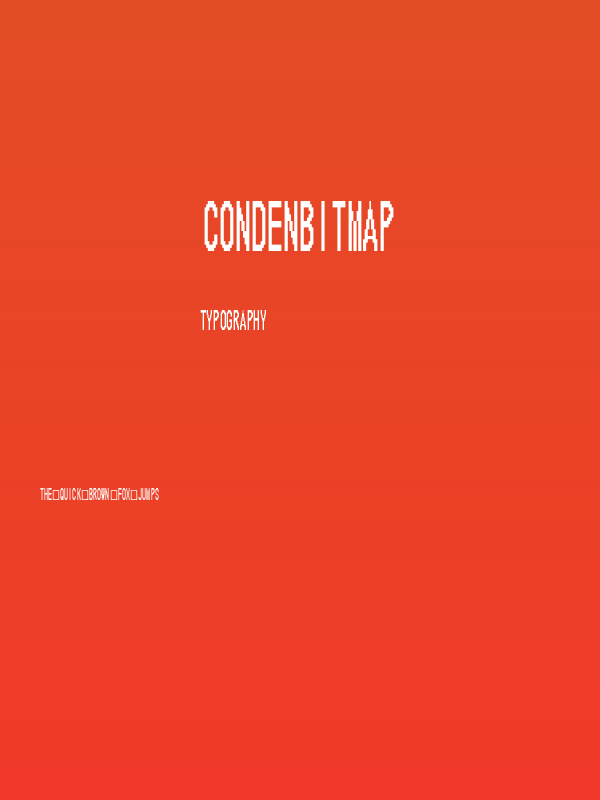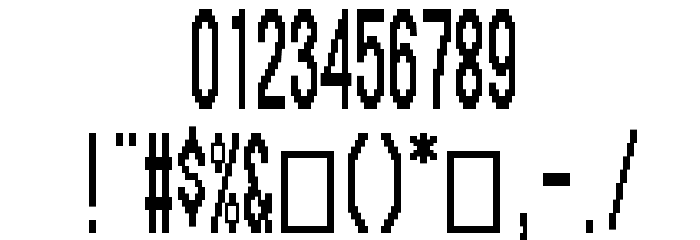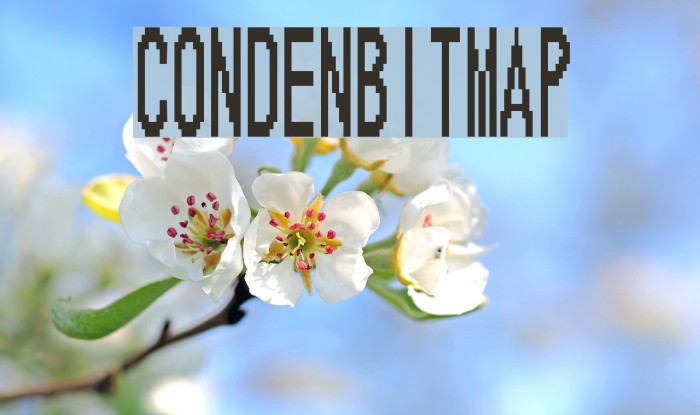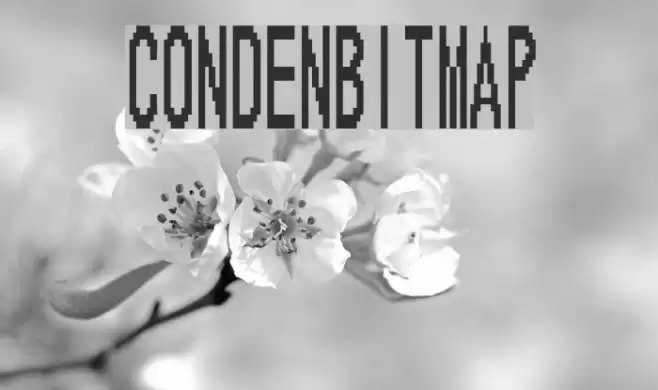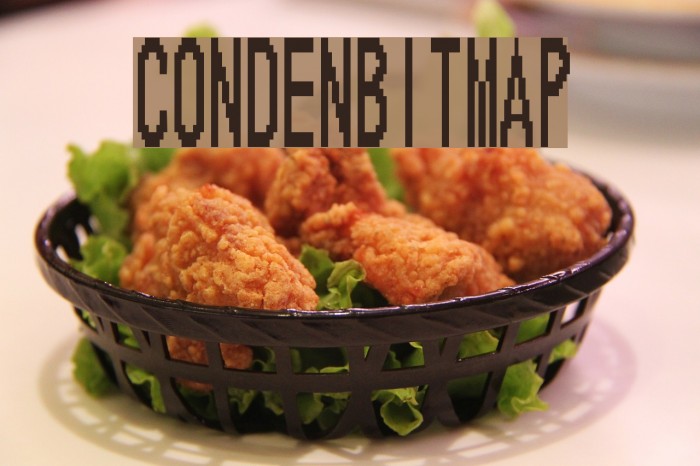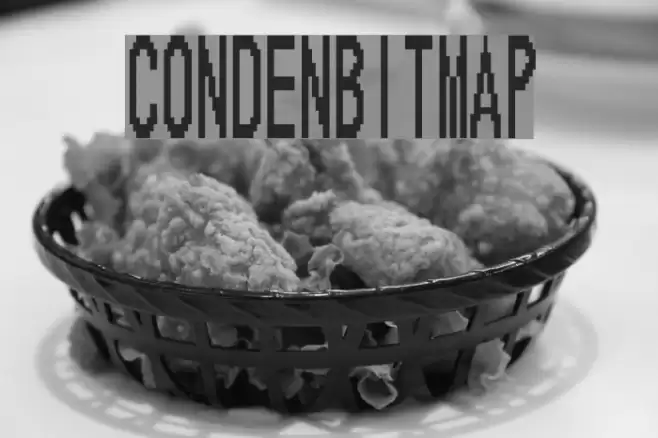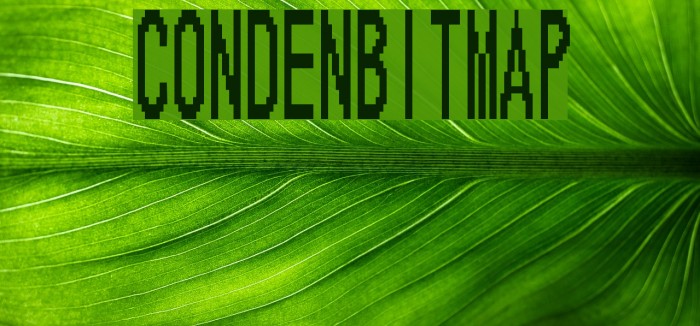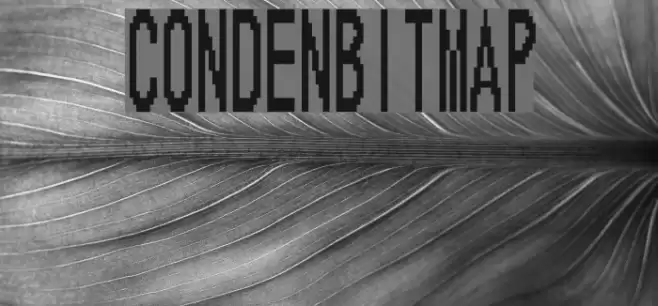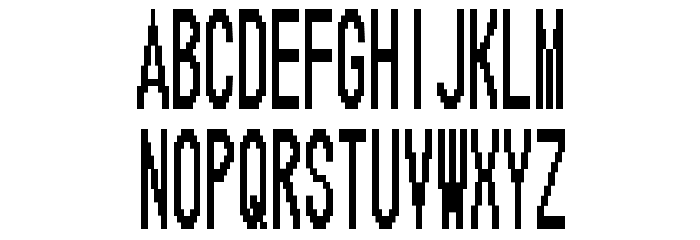
CondenBitmap Font
| श्रेणियाँ | Pixel |
| चौड़ाई | Condensed |
| समग्र शैली | Retro |
| उपयोग का मामला | Logos, Digital displays, Video game text |
| सुझाए गए प्रोजेक्ट | Ideal for retro video games, tech-themed designs, digital art projects, and nostalgic branding. |